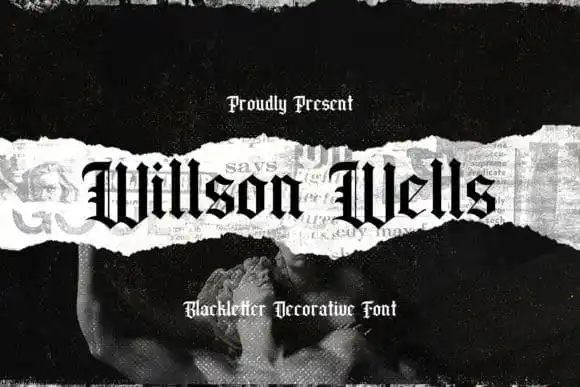
Wilson Wells Blackletter Font – Download Grátis
A ‘Wilson Wells Blackletter Font’ é uma tipografia inspirada no sub-texto de livros, criada para oferecer um estilo vintage combinando influências modernas e clássicas. Este tipo de letra blackletter traz alternativas incríveis que o tornam perfeito para adicionar um toque retrô especial a qualquer projeto gráfico que você possa imaginar! Possui uma aparência versátil, adequada tanto para criar logotipos quanto para desenvolver materiais publicitários como cartazes, revistas e até mesmo livros. Além disso, pode ser usada em coleções ou outros requisitos de design. Seja você um designer gráfico atento ao detalhe ou alguém que busca uma fonte única para suas criações digitais, ‘Wilson Wells Blackletter Font’ é a escolha certa. O conjunto completo desta font inclui tudo o que precisará para tornar seu projeto único e autêntico.